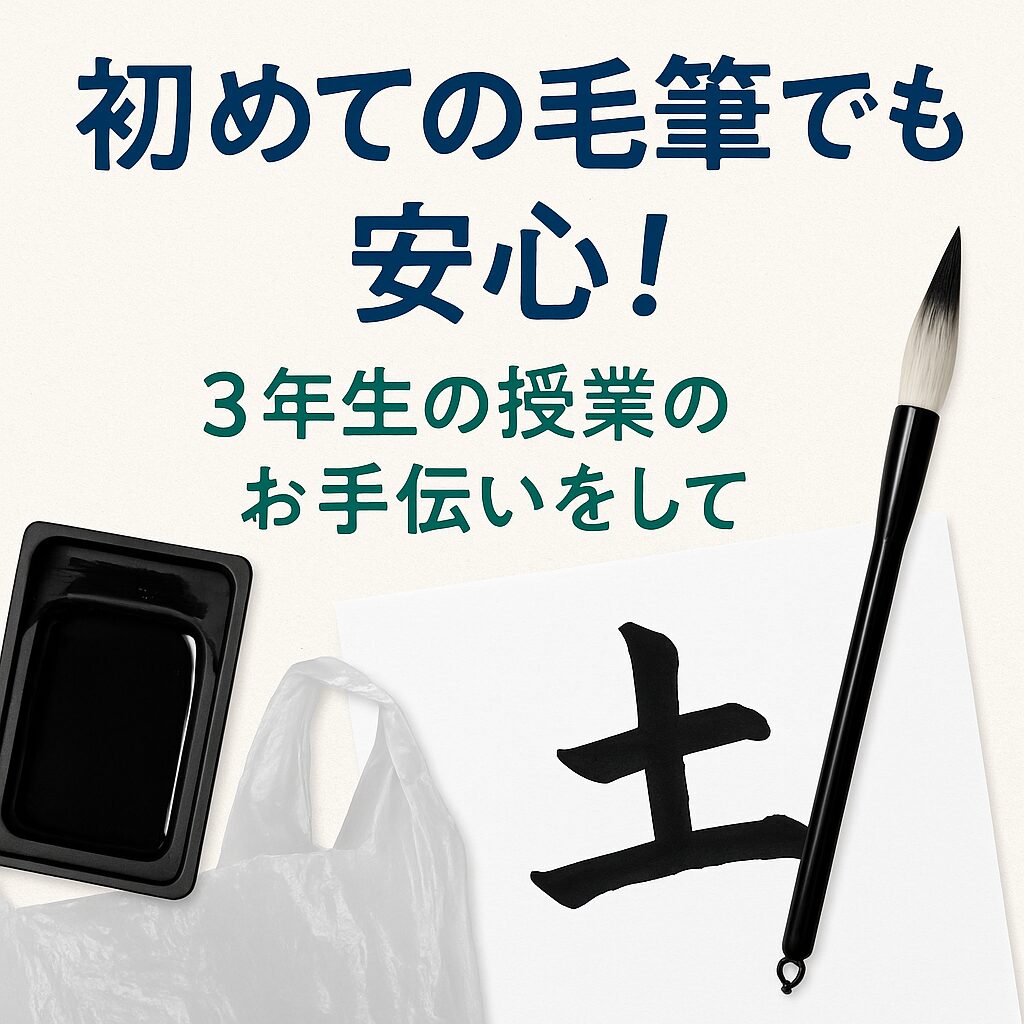
先日、学区内の小学校にお手伝いに行ってきました。小学校3年生の毛筆の授業です。練習していたのは、シンプルで奥の深い「土」の字。子どもたちのお手伝いをしながら、集中した表情や、うまく書けたときの笑顔にたくさんのエネルギーをもらいました。
その一方で、「あ、ここでつまずく子が多いんだな」「これを一言伝えられたら、もっと楽しく書けるかも」という場面にも何度も出会いました。
そこで今回は、授業で毛筆をしている若葉マークの小学生のために、書道教室の視点から「ちょっとしたコツ」をまとめてみたいと思います。といっても、難しいことではありません。筆の持ち方、ちょっとした姿勢、片づけの工夫など、どれもすぐにできることばかりです。
教室で子どもたちと関わってきた経験と、実際の学校で感じたことをもとに、毛筆授業を担当している先生にもお届けできたらと思っています。毛筆が「むずかしいもの」ではなく、「書けた!ってうれしい体験」になるように――そんな願いを込めて。
毛筆の授業、こんな場面を見かけました
初めての毛筆、ワクワクドキドキ「どう書けばいいのかな?」の気持ち
3年生の子どもたちが「土」の字に取り組んでいる姿は、見ていてとても微笑ましく、そして真剣でした。「どう書けばいいのかな?」「うまくかけてる?」と、ドキドキワクワクな気持ちが伝わってきます。初めての毛筆に戸惑いながらも、一文字一文字に向き合うその姿に、こちらまで背筋が伸びる思いでした。
よくあるつまずき①:筆を寝かせてしまう → 筆を立てて持つ
その中で、共通して見られたのが「筆の持ち方」です。どうしても鉛筆のように斜めに寝かせてしまう子が多く見られました。毛筆は、筆を立てて持つことで、筆の穂がしっかり紙に触れ、線にメリハリが出てきます。
斜めに持っていると、横線や縦線は書ける(むしろ書きやすい?)かもしれませんが、後々払いや結びの筆運びができなくなってしまいます。
「筆の軸は天井に向けるくらい立てて書くと、ぐっとかっこよくなるよ!」と声をかけると、すぐに真似してくれる子もいました。子どもたちの吸収力は本当にすごいですね。
よくあるつまずき②:終筆をすぐに離してしまう → 2秒止まって最後に穂先
もうひとつ目立ったのが、書き終わりの「終筆」の部分。サッと筆を離してしまう子が多く、最後の線がギザギザになったり、止めの形がふわっと崩れてしまったりしていました。
「最後に2秒止まってゆっくり持ち上げる、穂先が最後だと、きれいに終われるよ」と伝えると、子どもたちも納得の表情で練習に取り組んでくれました。この“2秒の間”があるだけで、字の印象がまったく変わってくるんです。
毛筆の授業での子どもたちの様子
授業で出会った3年生たち。筆の持ち方に悩んだり、墨汁を戻すのに手間取ったりしながらも、一字一字と一生懸命に書いていました。
「どう書いたらいいんだろう?」「これで合ってる?」と、ちょっと戸惑いながらも、真剣に考えている様子がとても印象的でした。
うまく書けたときの顔、納得いかなくて何度もやり直す姿、みんなそれぞれ。上手に書けるかどうかだけじゃなく、「ちょっとやってみようかな」と思える時間になっていたらいいな、と静かに願っています。
子どもたちのそんな一コマを見られたこと、私にとっても貴重な経験になりました。